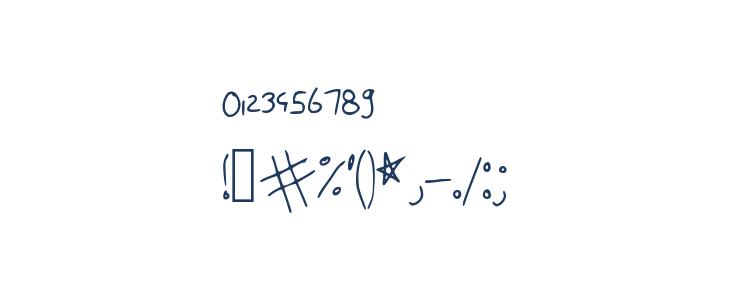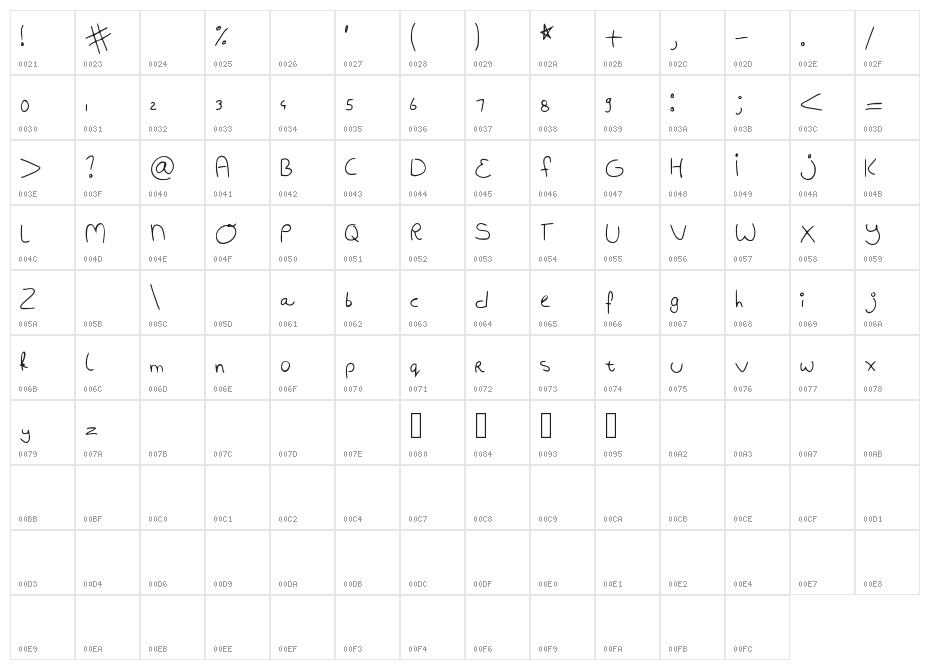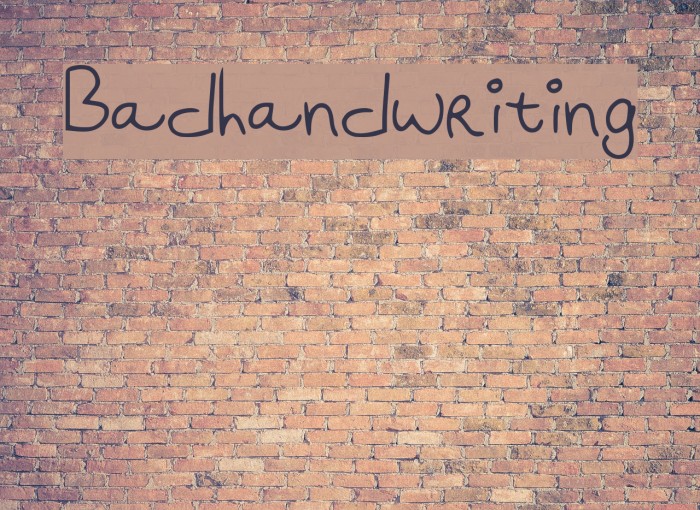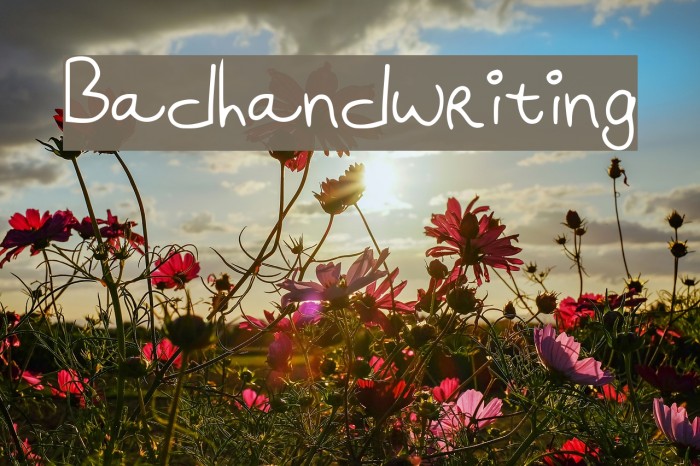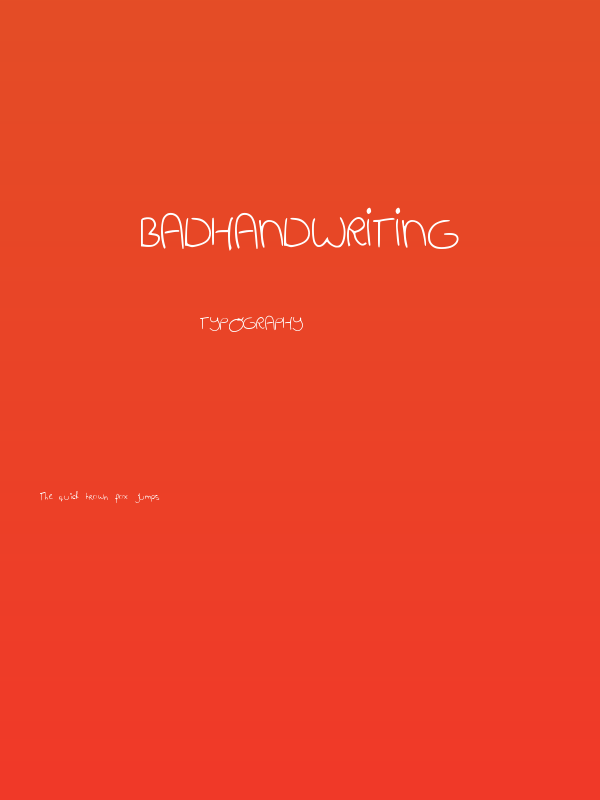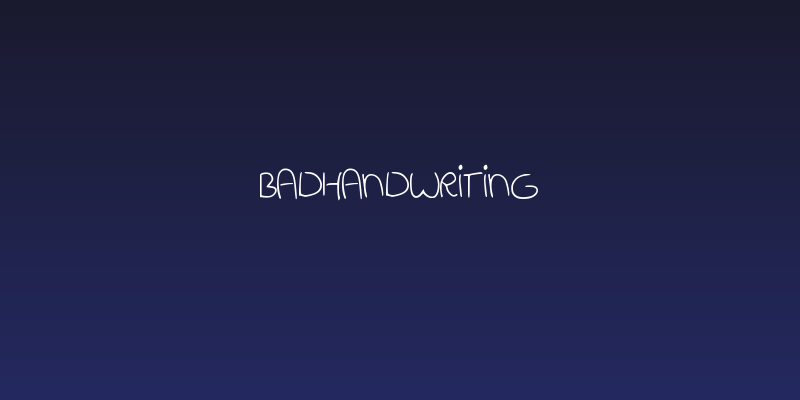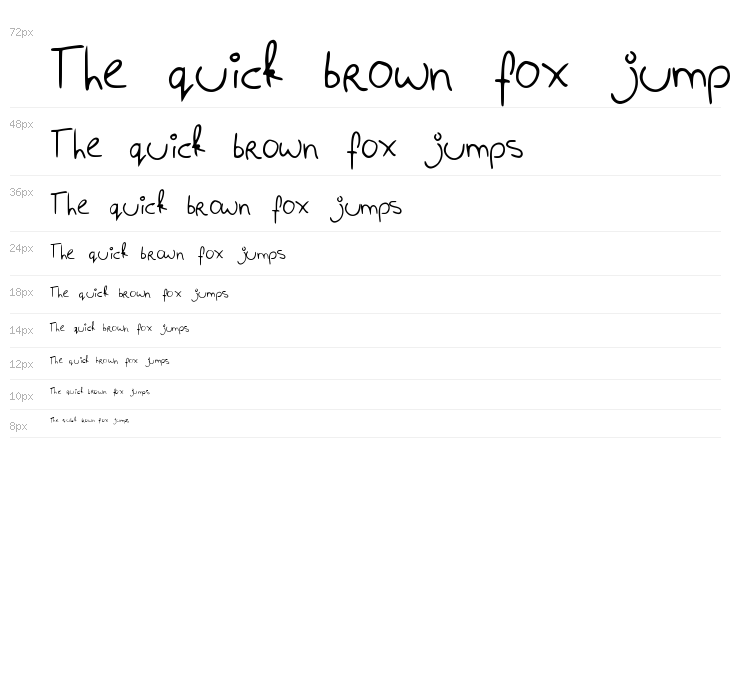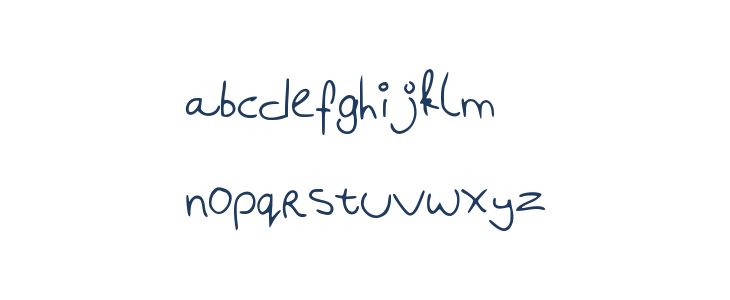
Badhandwriting Font
Ellen Landman
| Gesamtstil | Casual, Playful |
| Anwendungsfall | Headlines, Informal text, Personal projects |
| Vorgeschlagene Projekte | Ideal for greeting cards, personal invitations, children's books, and informal branding. |